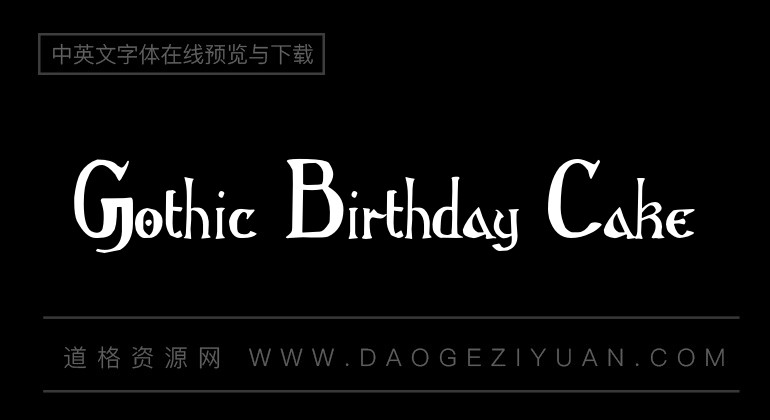
"Gothic Birthday Cake" 是一种装饰性字体,主要用于生日庆祝场合。这种字体的特点是它的线条粗细不一,有些线条相对较粗,有些相对较细,而且字母形状非常流畅和华丽,适合用于卡片、海报和其他与生日庆祝有关的设计中。 这种字体的设计灵感主要来自于哥特式字体,这是一种在中世纪欧洲广泛使用的书法字体,以其流畅的线条和华丽的装饰而闻名。"Gothic Birthday Cake" 字体采用了这种传统的设计元素,并将其与现代设计风格相结合,以创造出一种独特的装饰性字体。 "Gothic Birthday Cake" 字体可在许多免费字体网站上免费下载,可以安装在计算机上,以便在各种设计软件中使用。如果你正在寻找一种与众不同的装饰性字体来增添生日庆祝的氛围,那么这种字体可能正是你所需要的。内容介绍
Gothic Birthday Cake是一款非常不错的手写艺术字体,具有很好的视觉感,适合于文化类的宣传设计、商业类品牌的广告和产品包装设计以及个性化文字排版等较多场景。